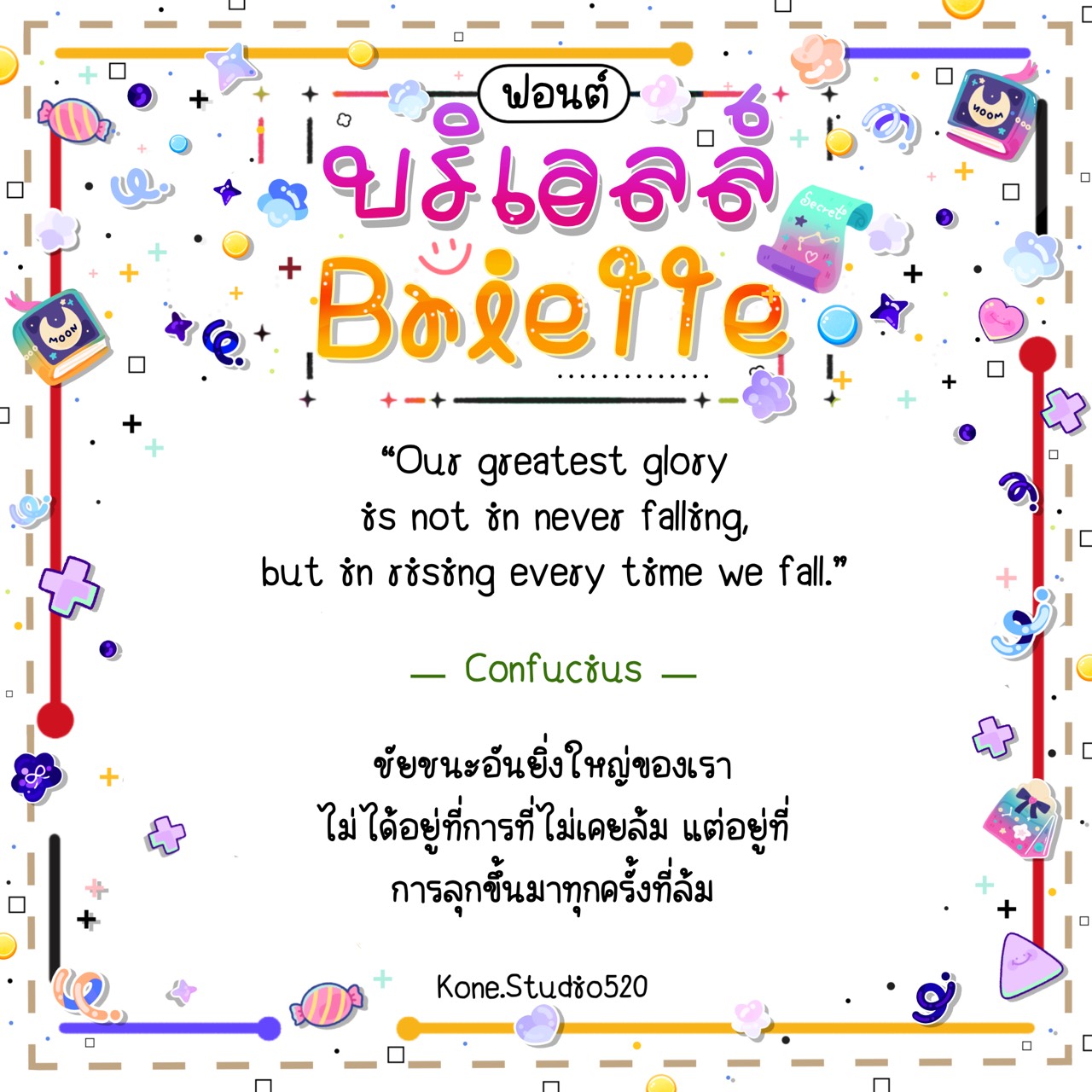
Kone.Studio520
ฟอนต์บริเอลล์ ( Brielle ) – แจกฟรี เวอร์ชันสำหรับทดลองใช้งาน (Demo)
ไฟล์แจกฟรี  (Demo) เป็นเวอร์ชันทดลองใช้งาน ยังไม่ได้ปรับสระ
ตัวอักษรบางส่วนอาจมีไม่ครบ อักษรใส หรือขนาดไม่เท่ากัน หากต้องการใช้งานแบบเต็มประสิทธิภาพ แนะนำให้ซื้อเวอร์ชันเต็มค่ะ✨